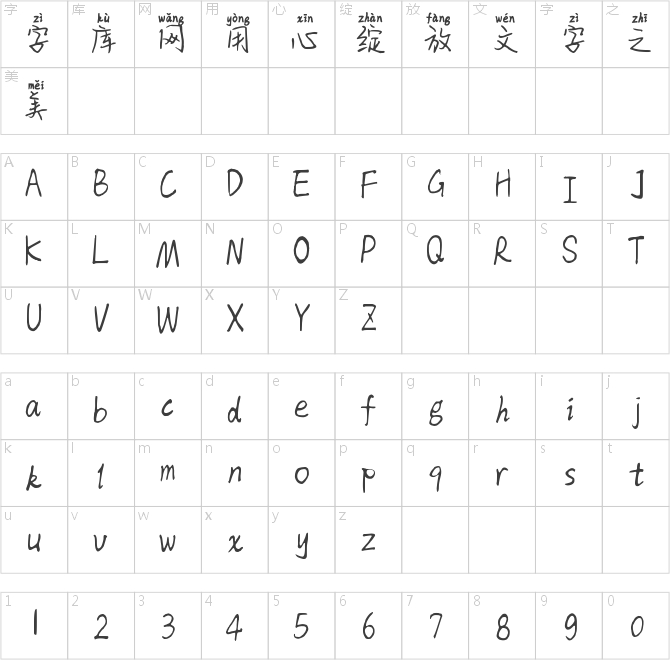
溫酒煮茶拼音體 詳情頁
字體名稱: 溫酒煮茶拼音體
溫酒煮茶拼音體
溫酒煮茶拼音體介紹
溫酒煮茶拼音體字體字庫是一款讓人賞心悅目、百看不厭的中文字體,適合各類廣告和產(chǎn)品包裝設(shè)計應(yīng)用,字體大小6.97MB,格式為ttf字體,上傳用戶是文道字庫,作者/版權(quán)方為文道